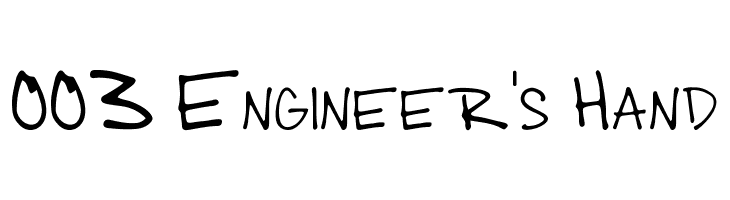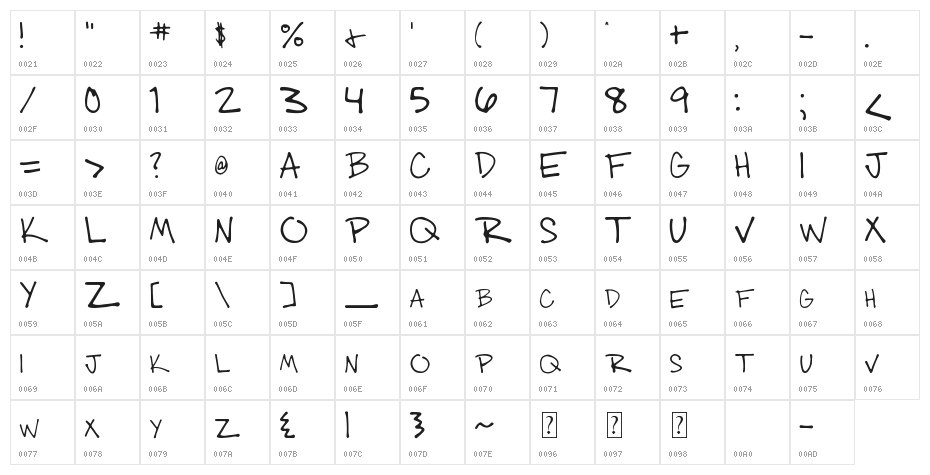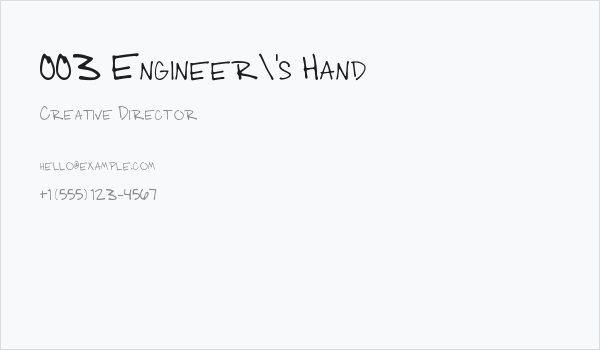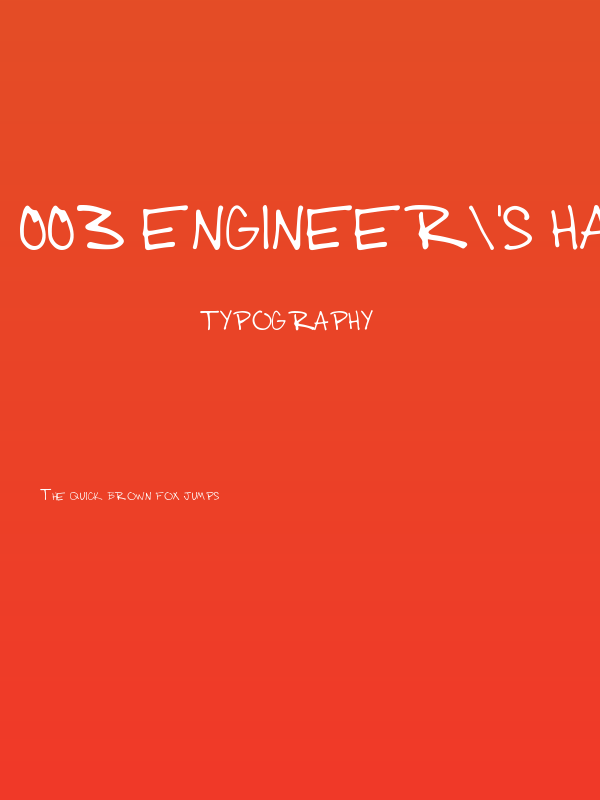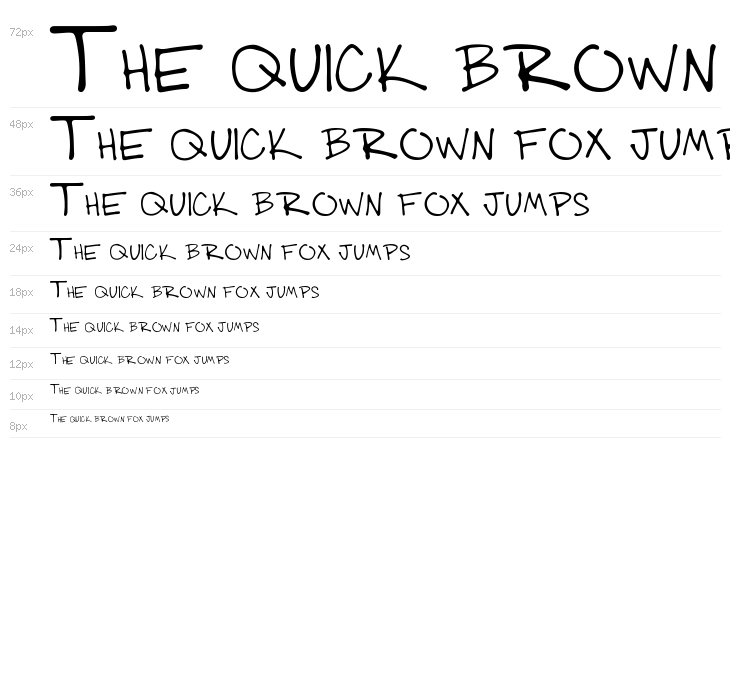
003 Engineer's Hand Font
| Estilo geral | Casual, Informal |
| Caso de uso | Personal notes, Creative projects, Informal invitations |
| Projetos propostos | Ideal for personal notes, informal invitations, educational materials, and creative projects that require a human touch. |